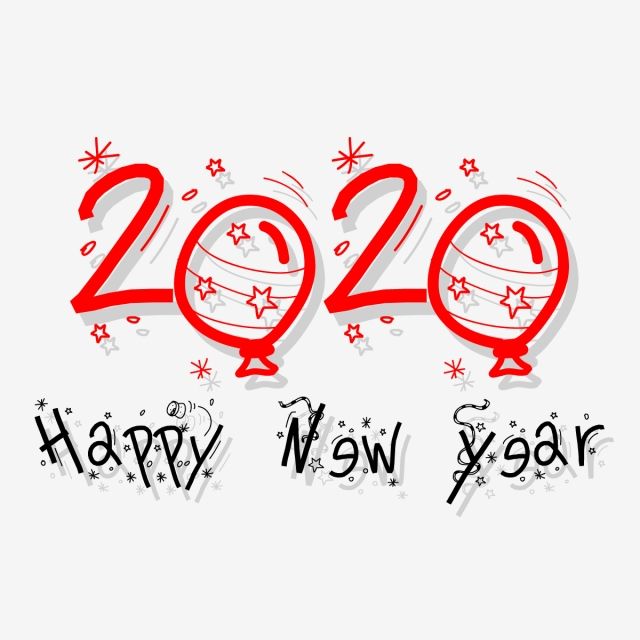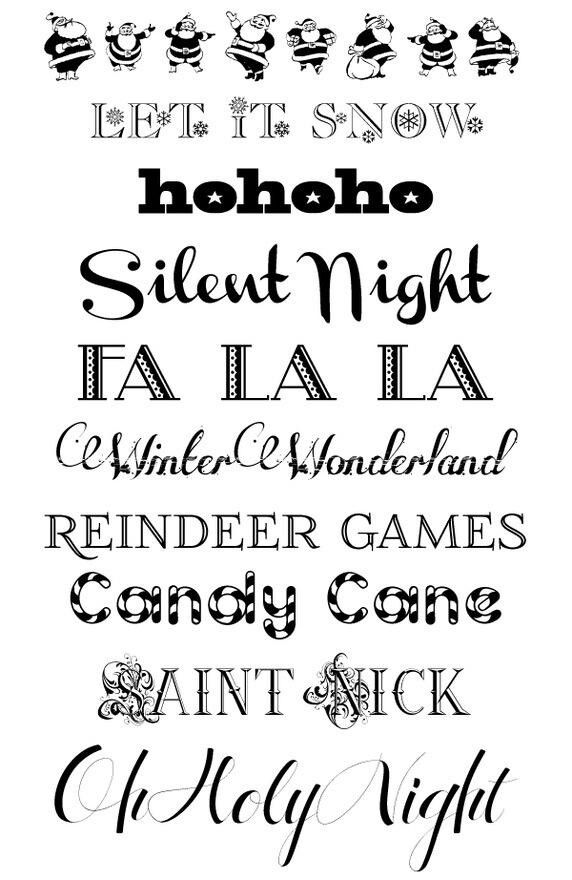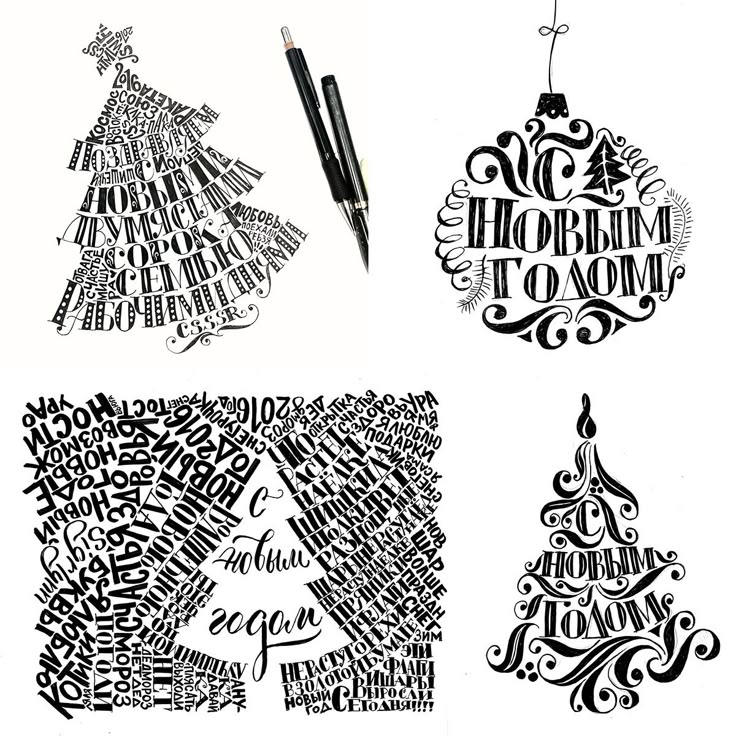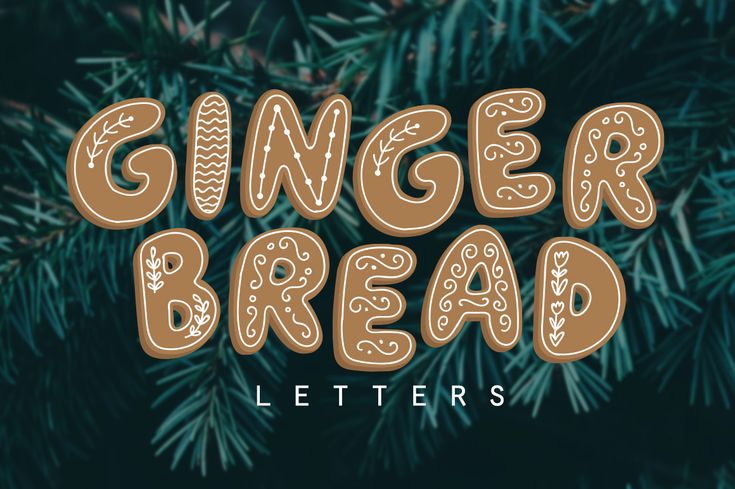
Добавляйте рождественские шрифты
Если вы используете его в качестве генератора зимних шрифтов, попробуйте стиль шрифта снег, текстовый эффект зимы и стиль шрифта замороженный.
Какие шрифты лучше всего подходят для Рождества?
Для этого времени года есть несколько шрифтов, которые работают лучше всего. Некоторые из них можно найти онлайн в MockoFun :
- Зимние шрифты
- Шрифт Happy Christmas
- Снежные шрифты, такие как шрифт Big Snow
- Ёлочная купель
- Вязаный уродливый свитер шрифт
- Рождественский шрифт
- Шрифт Snowy Christmas и т.